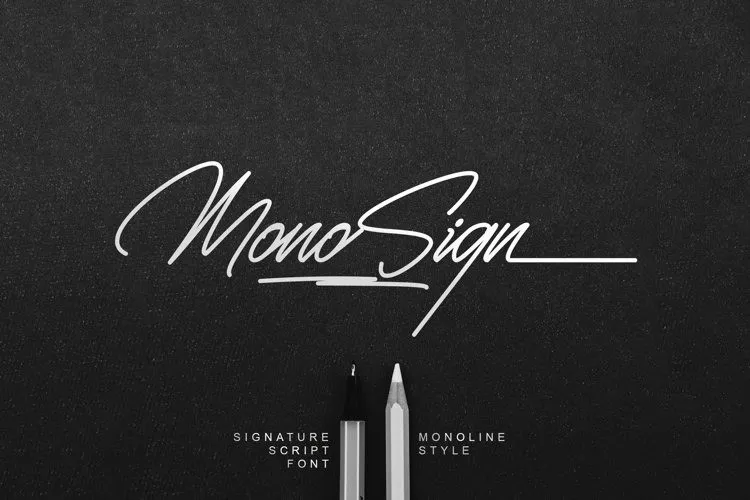
Monosign Script Font – Download Grátis
A Monosign Script Font é uma linda fonte criada a mão por lemonthe, especializada no estilo monoline. Ela oferece um toque elegante e sofisticado perfeito para destacar seus designs de forma elegante ou simplesmente dar um toque de classe. Esta fonte se destaca em várias aplicações, desde logotipos e marcas, cartões de convite e identidade visual, até postagens no Facebook e anúncios. Ela também é perfeita para embalar produtos, etiquetas e materiais publicitários, bem como incorporar um toque especial em fotos ou vídeos. Além disso, a Monosign Script Font também inclui vários swashes e caracteres especiais com apenas alguns cliques por sua PUA (Private Use Area) encodada. Essa característica permite que você manipule facilmente todos os símbolos e desenhos da fonte de maneira intuitiva para personalizá-la conforme necessário, seja em um design pessoal ou profissional. Para quem está sempre buscando aperfeiçoar seu trabalho gráfico, esta é uma excelente escolha. A Monosign Script Font pode ajudar você a expressar sua marca e arte com estilo único e sofisticado.